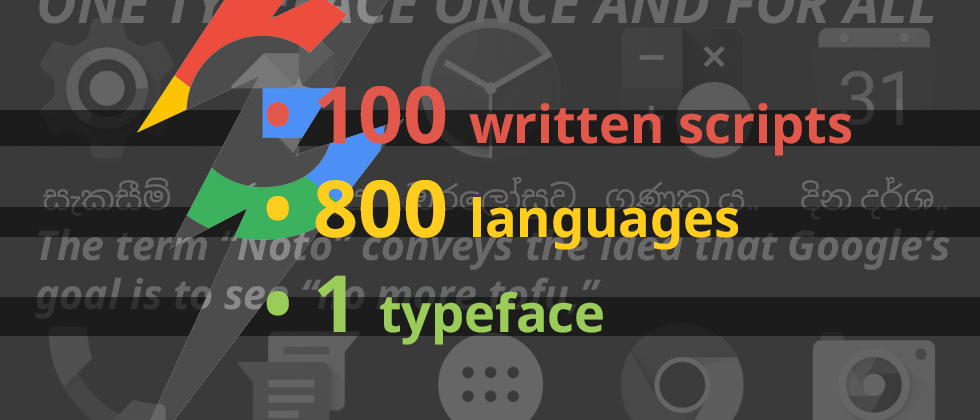
Khám Phá Noto, Bộ Font Chữ Google Tạo Ra Hỗ Trợ đến 800 Ngôn Ngữ ...
Một điều thú vị sẽ xảy ra khi máy tính hay điện thoại của bạn không thể hiển thị một nét chữ (font) nào đó: Một hình chữ nhật rỗng sẽ thay thế cho nét chữ mà máy tính không có. Hình hộp nhỏ này được gọi là .notdef, hay “không xác định” trong tiếng lóng của dân lập trình, nhưng mọi người thường gọi nó là tofu hay “đậu phụ”.
Trong khi đó, Bob Jung ghét đậu phụ. Sự thù ghét của ông với với nó bắt đầu từ những năm 1980, khi ông sở hữu một chiếc máy tính Mỹ ở Tokyo. “Trong những ngày đó, nếu bạn mua một chiếc máy tính Mỹ, bạn sẽ không có nét chữ ở bất kỳ ngôn ngữ nào khác.” Ông cho biết. “Vì vậy, bạn sẽ thường xuyên phải ăn đậu phụ.”
Giờ ông đang dẫn dắt bộ phận Quốc tế hóa của Google, để đảm bảo các sản phẩm của công ty có thể hoạt động ở mọi nơi. Nhóm của ông dành ra 6 năm để làm việc với các nhà thiết kế tại Monotype nhằm loại bỏ hình đậu phụ khỏi các thiết bị của Google bằng một bộ nét chữ (font) gắn kết với nhau cho nhiều loại ngôn ngữ, được gọi là Noto (viết tắt của “No more tofu” – không còn đậu phụ).
Noto, một trong các đại gia đình chữ in máy với quy mô rộng nhất từng được tạo ra, khi nó hỗ trợ đến 800 ngôn ngữ, 100 loại chữ viết (script) trong 8 kiểu đậm nhạt khác nhau, vô số các ký tự đặc biệt, và hoàn toàn không có đậu phụ.
Noto giải quyết một vấn đề hữu ích quan trọng mà phần lớn mọi người thậm chí còn không biết nó tồn tại. Khi bạn viết bằng các ngôn ngữ như tiếng Anh, tiếng Hindi, tiếng Trung phổ thông, hay tiếng Nga, bạn hiếm khi phải thấy những miếng đậu phụ. Những ngôn ngữ như vậy được hỗ trợ bởi Unicode, tổ chức này phê duyệt các emoji (biểu tượng cảm xúc) và duy trì các phần mềm theo tiêu chuẩn quốc tế hóa, và vì vậy thiết bị của bạn cũng sẽ được hỗ trợ.
Nhưng mọi người đọc và viết bằng hàng trăm ngôn ngữ khác nhau. Đến gần đây, Unicode mới phê duyệt tiếng Tibetan (Tây Tạng), cũng như tiếng Armenian. Vẫn còn rất nhiều ngôn ngữ khác đang đợi được phê duyệt. Nếu những ngôn ngữ ít phổ biến này cần có một kiểu chữ (typeface) kỹ thuật số, nó có thể không được xem xét đến, bởi vì “một số khu vực trên thế giới có truyền thống về tạo chữ in máy (typographic) phong phú hơn những khu vực khác.” Steve Matteson, giám đốc sáng tạo của Monotype cho biết.
Steve Matteson là người dẫn dắt hàng trăm nhà nghiên cứu, nhà thiết kế, và các nhà ngôn ngữ học, để mang lại cho mỗi chữ viết tương thích với Unicode một nét chữ (font), và đảm bảo những nét chữ này sẽ như một phần trong cùng một đại gia đình chữ in máy.
Trước đây, các nền tảng thường cấp phép những nét chữ theo từng loại chữ viết khác nhau, (vì một loại chữ viết có thể dùng cho một số ngôn ngữ – ví dụ, tiếng Anh, tiếng Iceland và tiếng Hà Lan chỉ là 3 trong số hàng chục ngôn ngữ dựa trên chữ viết Latin). Vì vậy, họ sẽ mua một loại cho các chữ viết Latin như tiếng Tây Ban Nha và tiếng Pháp, một loại chữ viết khác của ngôn ngữ Arabic, và một loại chữ viết khác nữa cho tiếng Nhật hay Trung Quốc.
“Bạn sẽ nhận được một mớ hỗn độn các nét chữ khác nhau.” Jung cho biết. “Đó là lời phàn nàn mà chúng tôi thường nhận được – các nét chữ trông không đẹp khi bạn kết hợp nhiều loại ngôn ngữ với nhau.” Việc phát triển một kiểu chữ cho 800 ngôn ngữ, cho dù gắn kết với nhau, nhưng nếu không tạo ra sự trân trọng với di sản văn hóa của mỗi ngôn ngữ đó, nó sẽ tạo ra sự căng thẳng vốn có.
Và vì vậy, việc làm cho những nét chữ đó có những phong cách “không thể nhầm lẫn của Google” là điều gần như không thể. Ví dụ, đường nét trong chữ viết Tây Tạng mang nặng kiểu viết chữ đẹp truyền thống, trong khi tiếng Anh nhiều nét thẳng và mang tính hình học hơn.
Kiểu chữ Tây Tạng với đường nét như lối viết chữ đẹp truyền thống.
Kiểu chữ Arabic thường viết đậm các nét theo hướng từ trái sang phải, trong khi các chữ cái tiếng Pháp lại thường viết đậm ở các nét sổ dọc trong chữ. Một vài nét chữ khác, như Runic, có quá ít người biết đến nỗi những người làm chữ in tại Monotype phải tự thiết kế kiểu chữ đó từ việc khắc theo cảm hứng.
Kiểu chữ Arabic với nét đậm từ trái sang phải, và kiểu chữ tiếng Pháp với nét đậm từ trên xuống dưới.
Mục tiêu là tạo ra một đại gia đình các nét chữ, ít nhất cũng có thể cho thấy mối quan hệ với nhau. “Chúng tôi muốn làm nó sao cho khi mọi người thay đổi các thiết lập ngôn ngữ của mình, họ sẽ không thấy giống như mình đang sử dụng một nền tảng hoàn toàn khác biệt.” Matteson cho biết.
Ông thiết kế Noto hiện đại nhưng vẫn thân thiện, với các nét cong mở, đuôi chữ mềm mại và nét bút như lối viết chữ đẹp từ thế kỷ thứ 5. Ông cũng tránh làm Noto trở nên quá đơn giản khô khan, khi phần lớn các hình dáng sẽ không thể hiển thị một cách đẹp đẽ khi chuyển sang một ngôn ngữ khác. “Không dễ để thể hiện những ngôn ngữ có chữ viết đẹp như tiếng Tây Tạng dưới mô hình kiểu chữ Futura, vốn chỉ gồm các vòng tròn và đường thẳng.” ông cho biết.
Bạn sẽ thấy một số hình dạng chung xuất hiện phổ biến giữa các nét chữ trong đại gia đình Noto. Mọi nét chữ đều có một nét đậm tương tự nhau, tạo nên một sự liên tục giữa các chữ. Và cho dù không phải mọi ngôn ngữ đều dựa trên đường cơ sở (baseline) và đường đỉnh (cap-line) tương tự nhau (ví dụ, các chữ cái trong ngôn ngữ châu Á có xu hướng cao hơn so với các chữ cái tương tự trong ngôn ngữ Latin), chúng đứng thành hàng với nhau để tạo nên một đường tưởng tượng có thể chia đôi các chữ cái Latin.